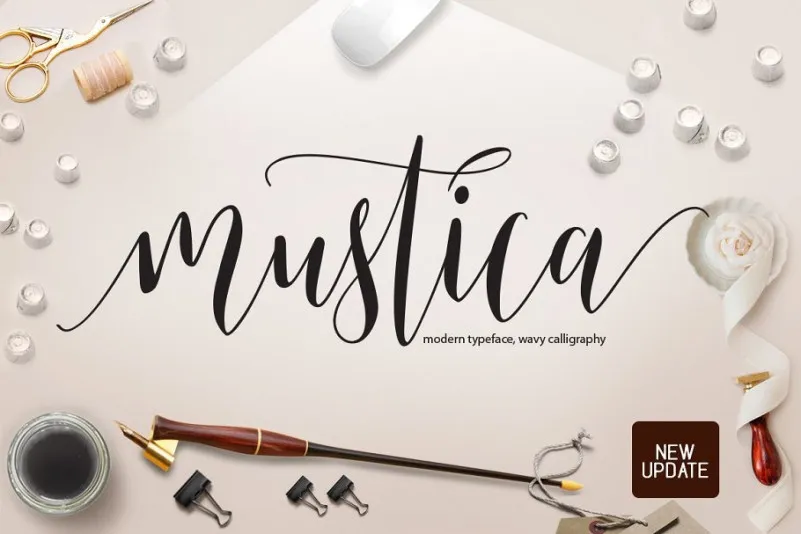
A Mustica Script Font é uma excelente adição para seu acervo de fontes, especialmente se você busca algo delicado e elegante. Desenvolvida pelo designer 178-MC, essa fonte vem na forma de escrita livre-marinha, com linhas finas e sutis que remetem à arte da caligrafia. Ideal para um estilo chamativo e sofisticado, ela foi projetada justamente para aquelas pessoas procurando por uma caligrafia extravagante. Introduzida no mercado de fontes modernas, essa escolha traz consigo um ar de elegância versátil, que transborda em sua escrita ondulada e sofisticada. Seu toque suave é perfeito para complementar seus projetos design como logotipos, cartazes impressos com citações, convites, cartões personalizados, embalagens de produtos, cabeçalhos e outros elementos da sua criatividade. Estas qualidades a tornam uma excelente opção para qualquer projeto onde deseja transmitir sofisticação. Sua presença enriquece sua composição visual, seja em design editorial, marca ou arte digital. Com apenas um clique, pode transformar seu trabalho de modo que reflita não só o seu profissionalismo, mas também a sua personalidade e estilo único.